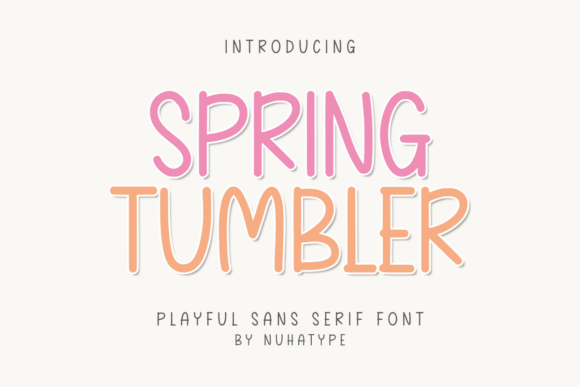
Spring Tumbler
適切なデザイン要素を見つけるのは難しい場合がありますが、Spring Tumblerは作品を即座に引き立てる優れたコレクションを提供します。
精密に作られたSpring Tumblerは、クリーンなベクター、滑らかなタイポグラフィ、そして安心のための商用ライセンスを提供します。
POD(オンデマンド印刷)製品、結婚式の招待状、またはソーシャルメディアのグラフィックを作成している場合でも、Spring Tumblerは理想的です。